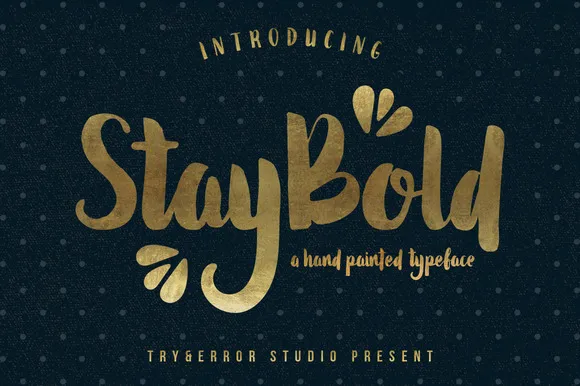
Stay Bold Typeface
Olá! Estou aqui uma linda oportunidade para você explorar a estética sofisticada e fluida do Stay Bold Typeface, uma fonte script moderna e brilhante. Conhecida por sua aparência trendy e desenhada à mão, essa fonte é perfeita para gráficos de alto nível. Suas linhas elegantes e curvas suaves garantem um visual atraente, que se destaca em diversos usos, desde cartões de visita até capas de livros e embalagens. Seja você designer ou criador de conteúdo, Stay Bold Typeface traz o toque final único para seus projetos. Não importa qual projeto você está lidando, essa fonte é uma escolha incrivelmente versátil que se adapta perfeitamente aos seu estilos. Adquira agora e transforme suas ideias em arte!